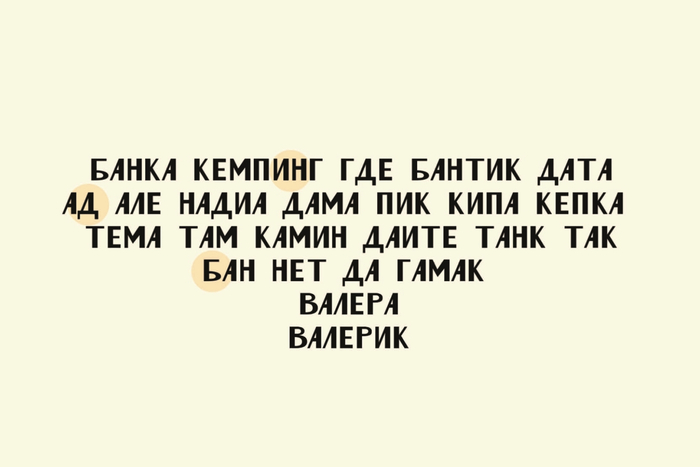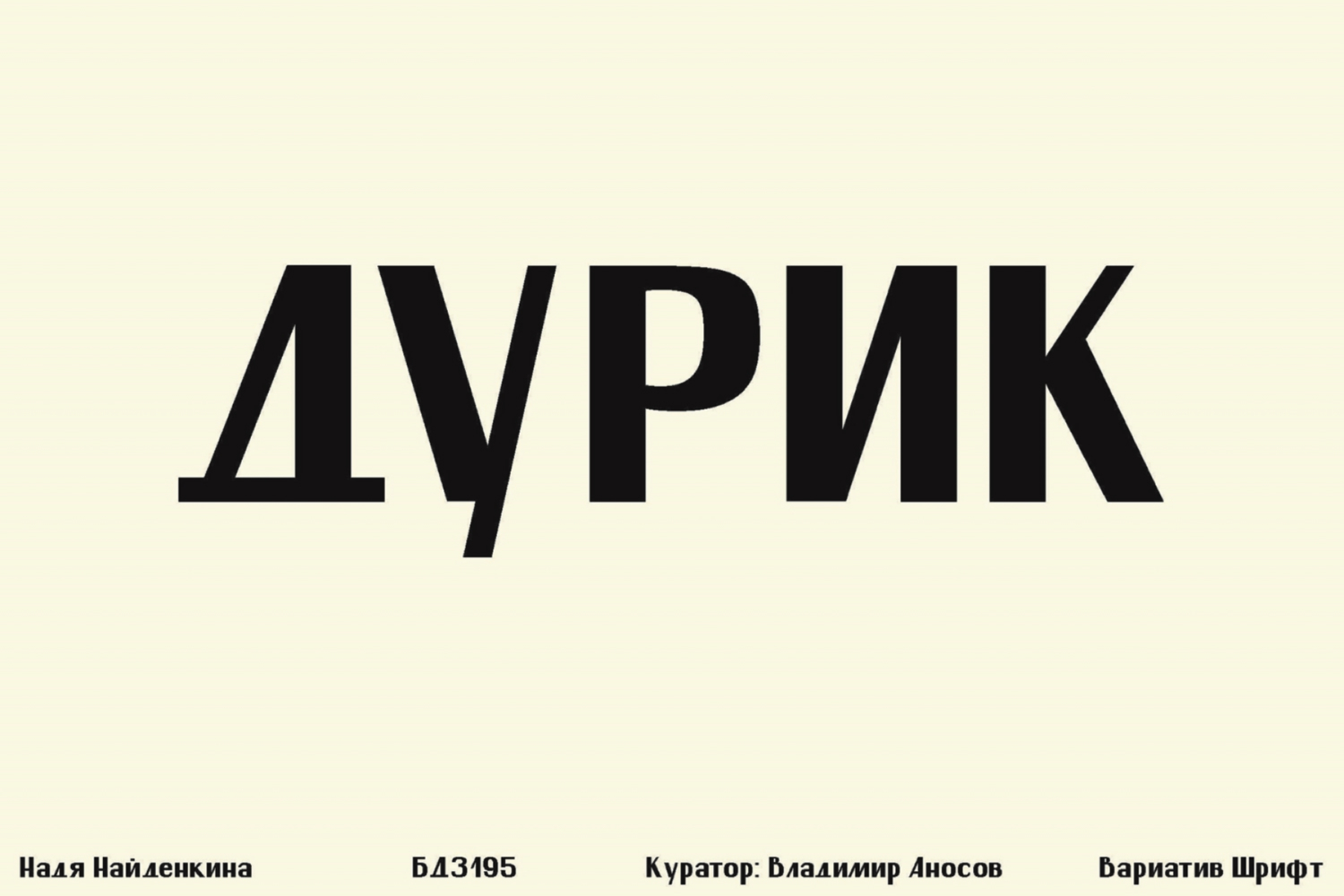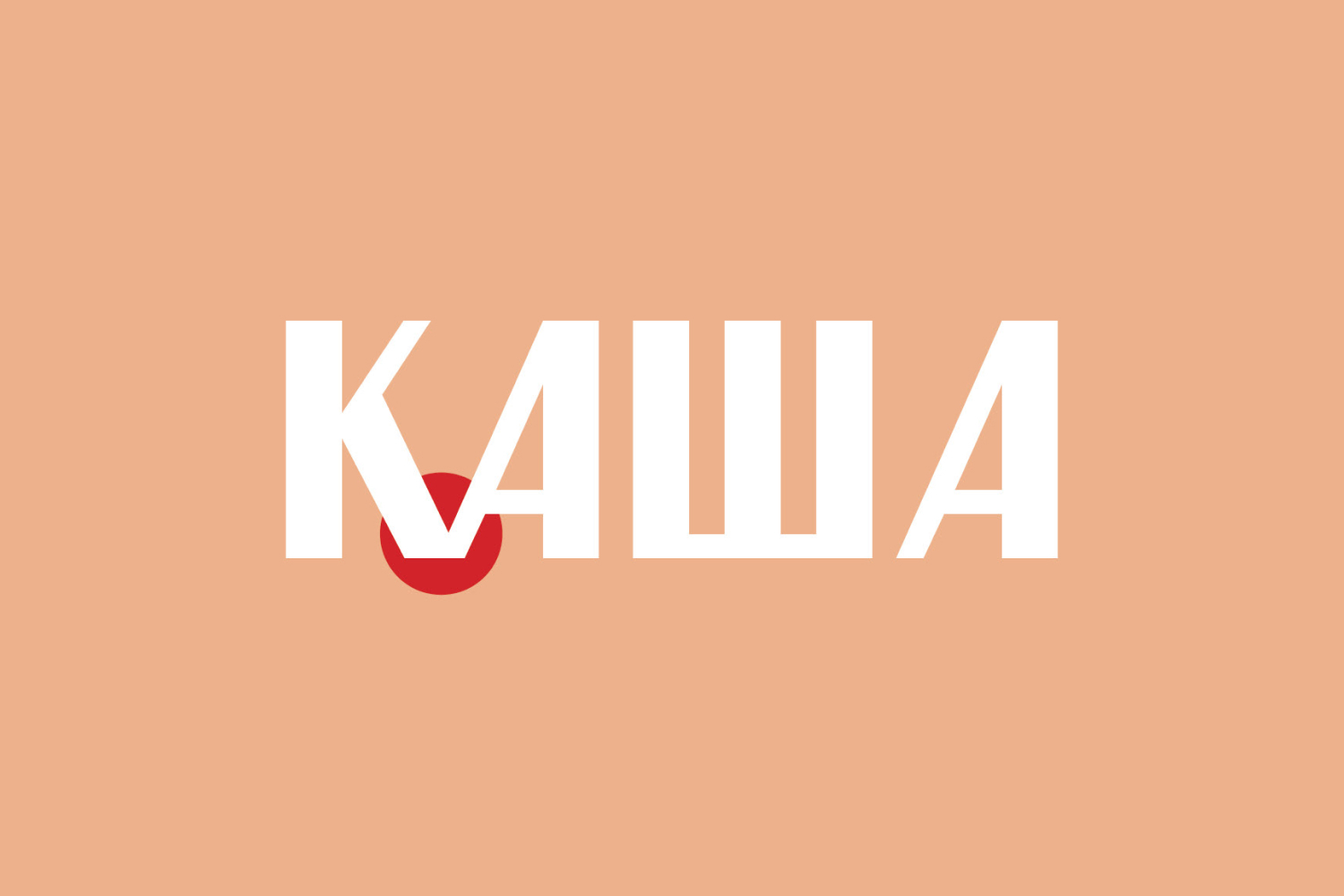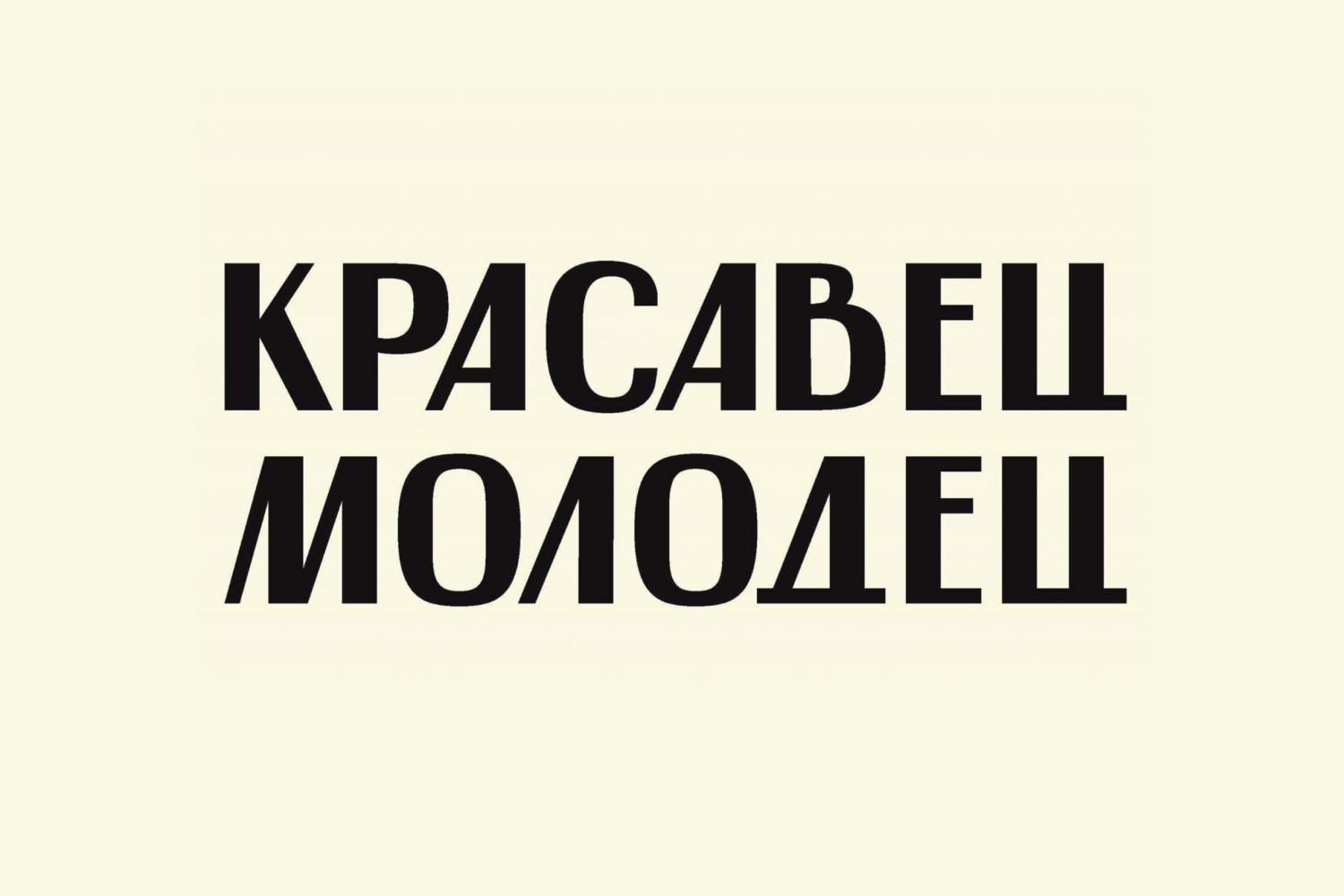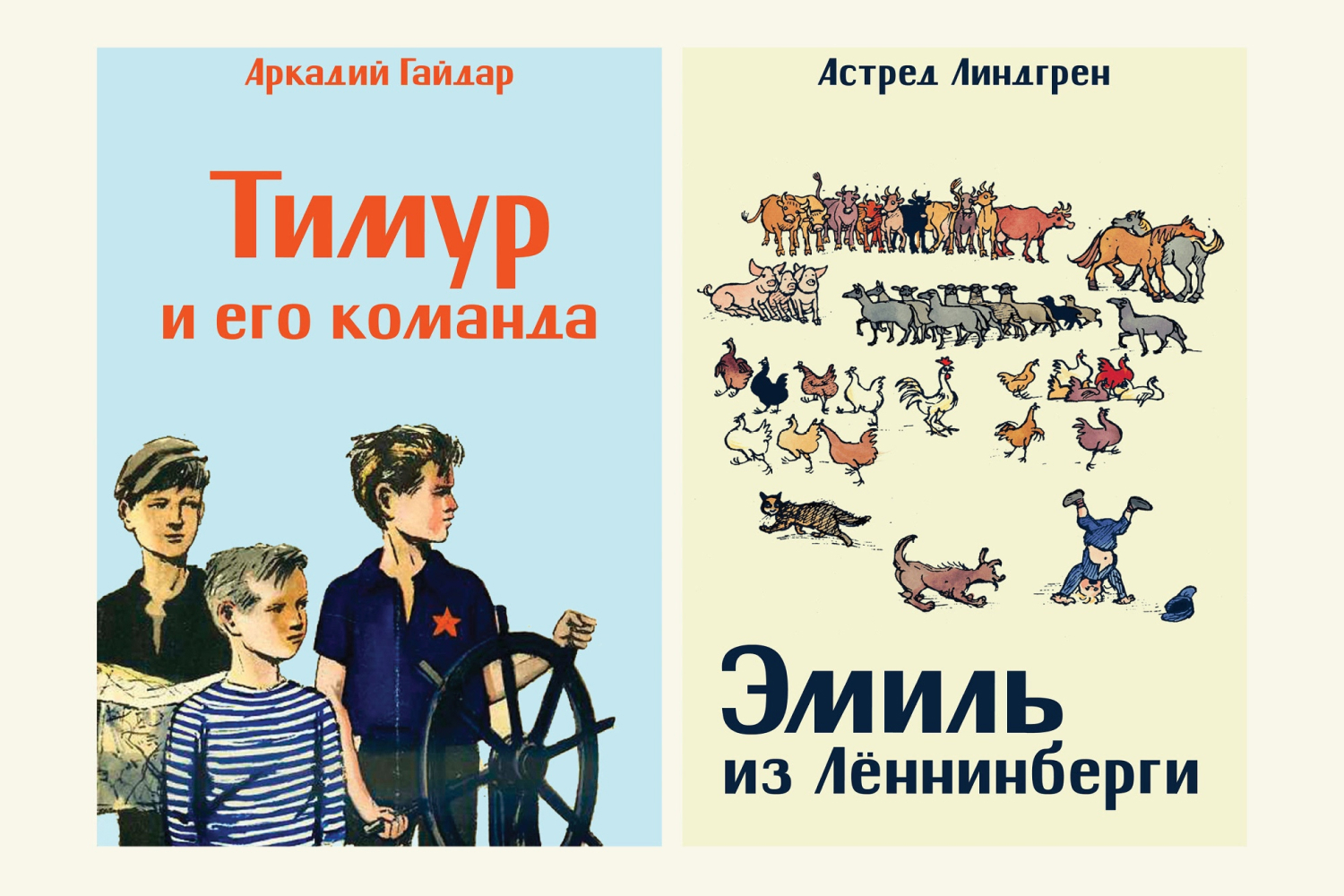
Бесплатный шрифт Дурик
Брусковый стиль. Похожий на кирпич. Прям можно взять его и кинуть в нехорошего человека. Идеально для плакатов)
Автор: Nadia Naidenkina
Брусковый стиль. Похожий на кирпич. Прям можно взять его и кинуть в нехорошего человека. Идеально для плакатов)
Автор: Nadia Naidenkina